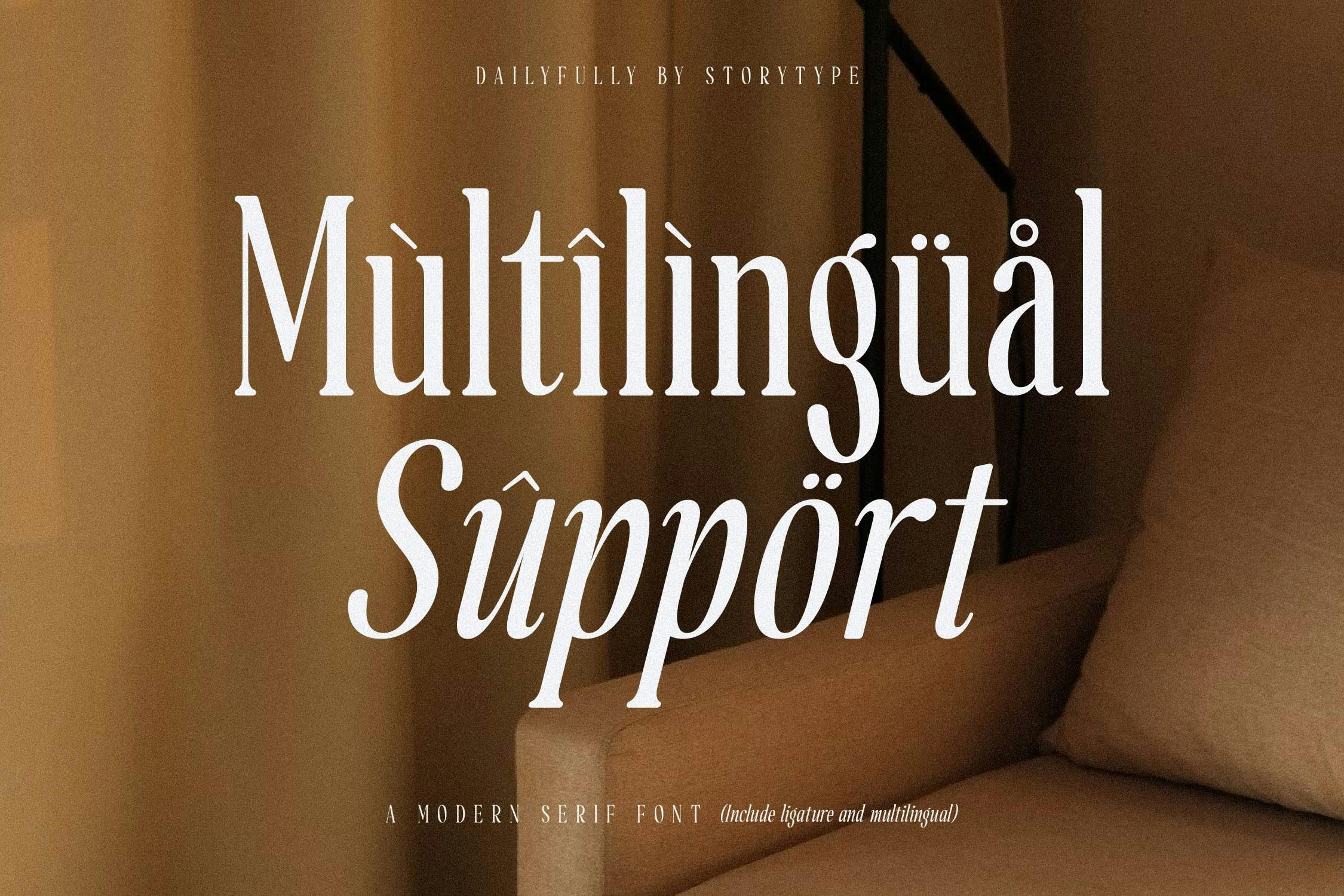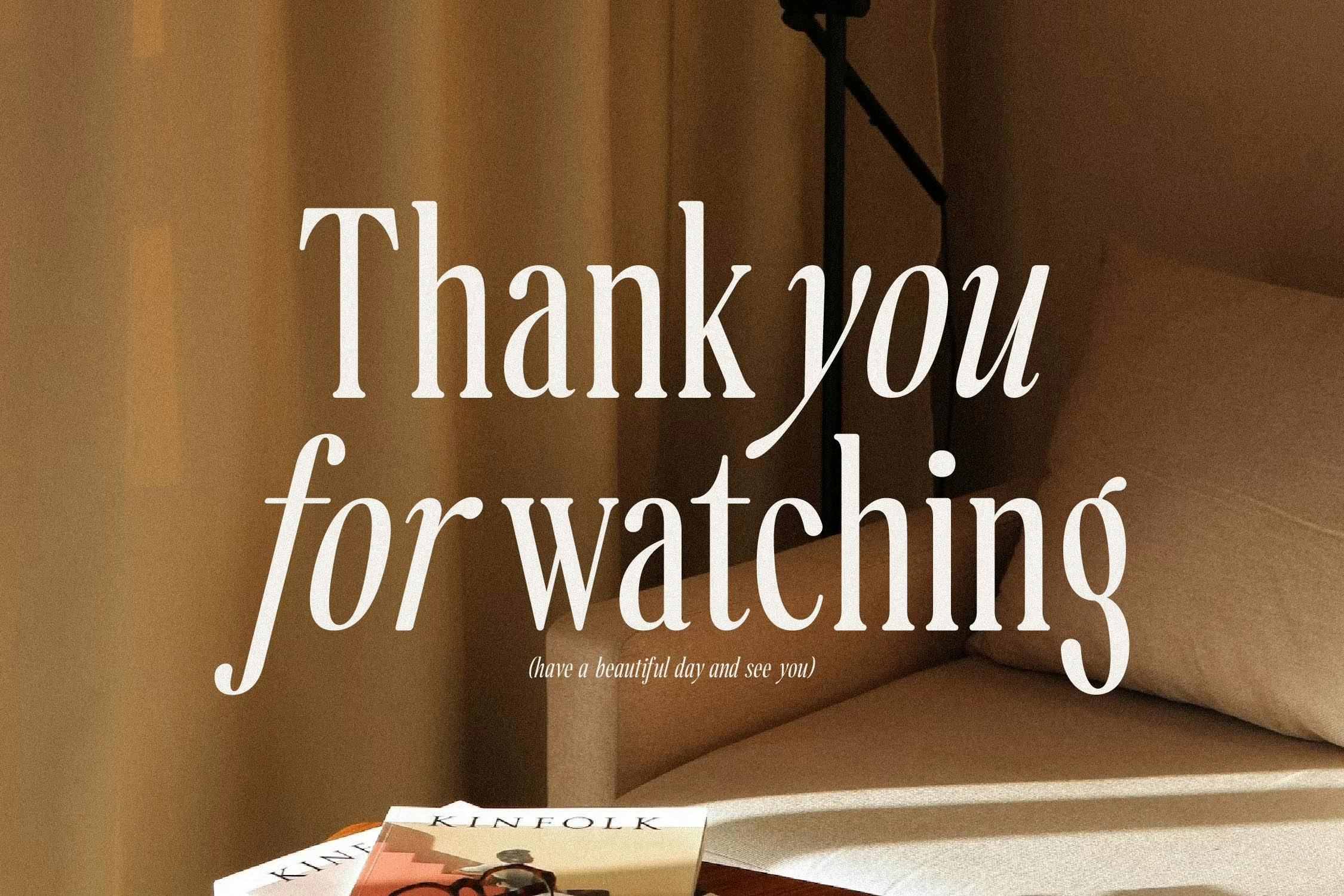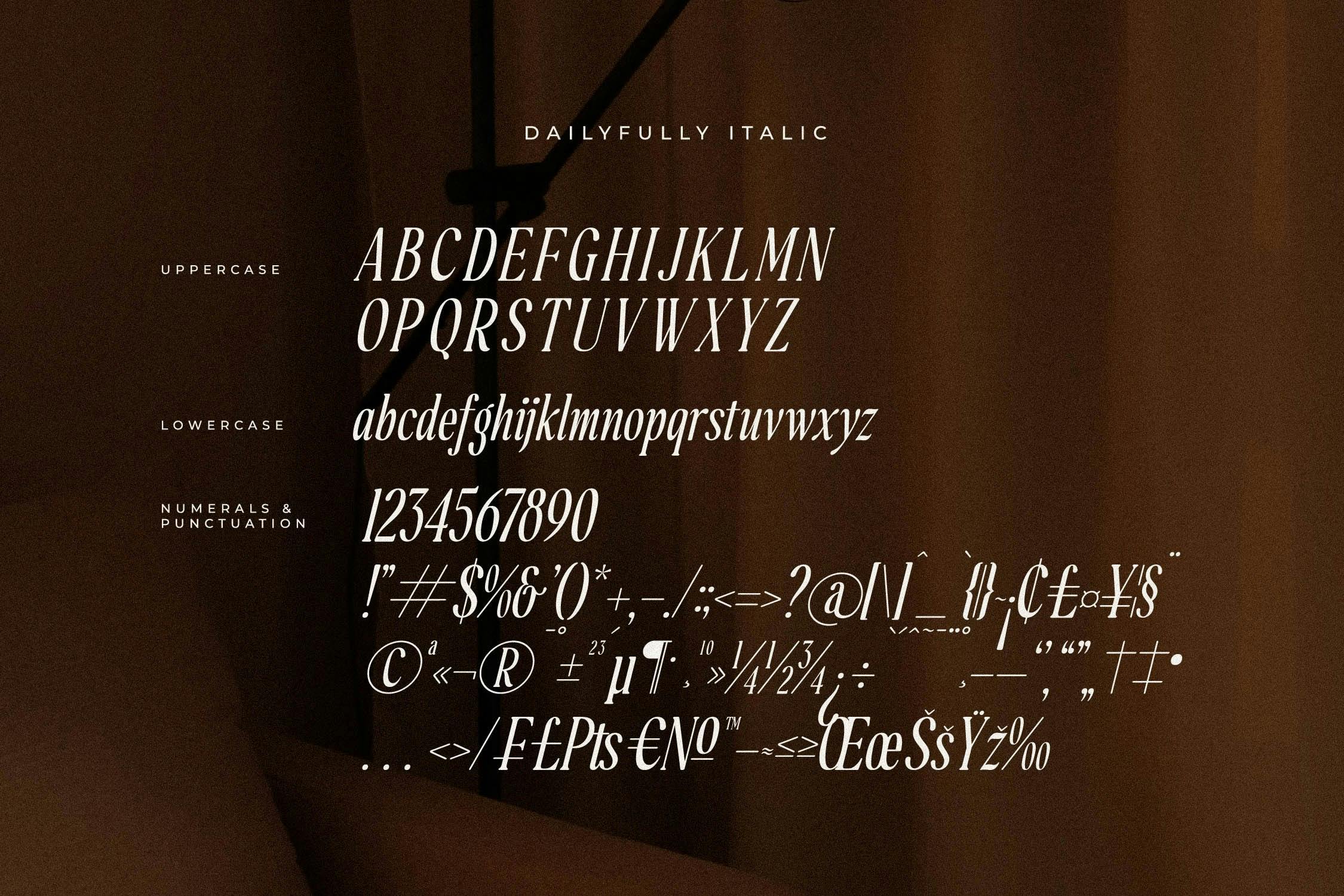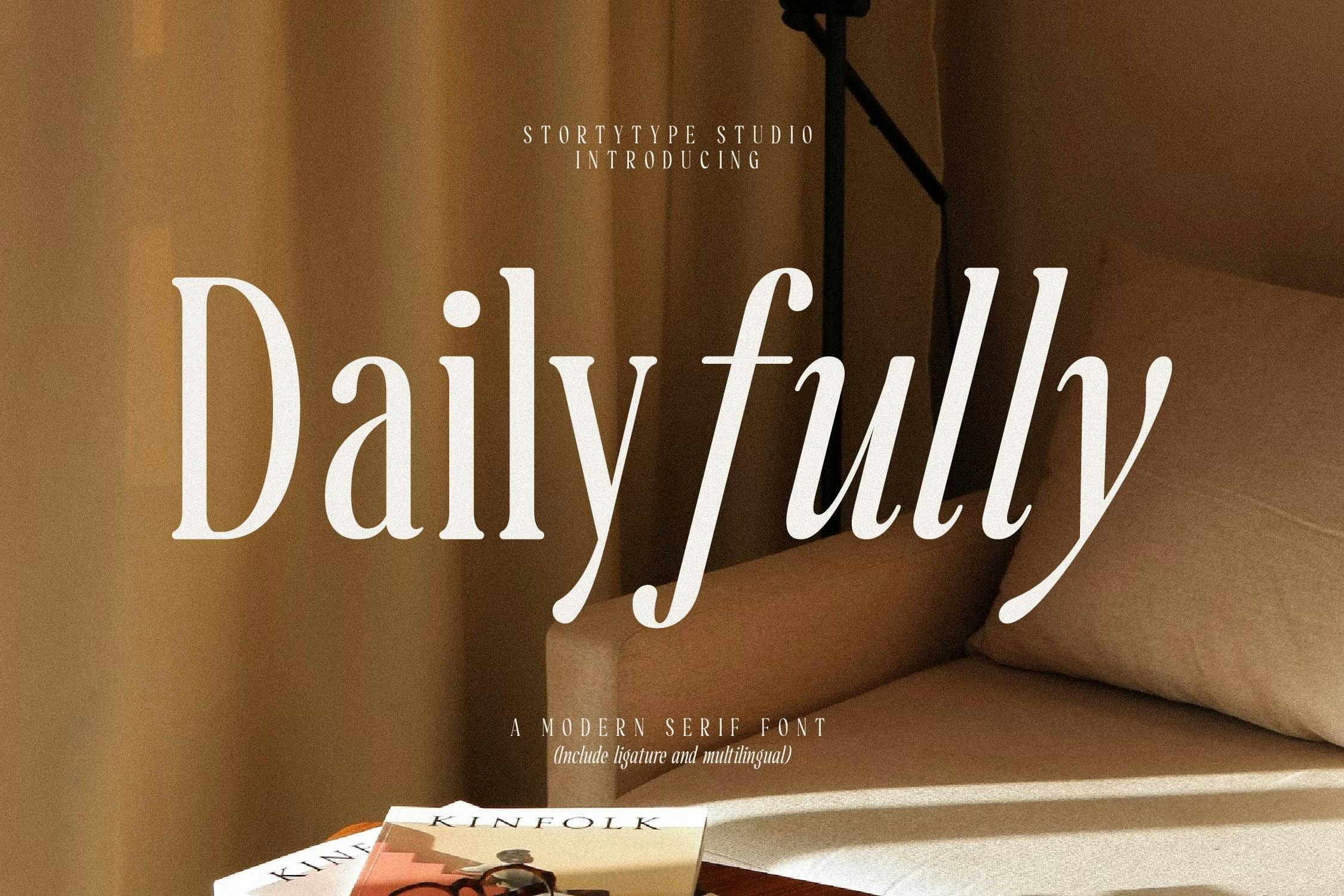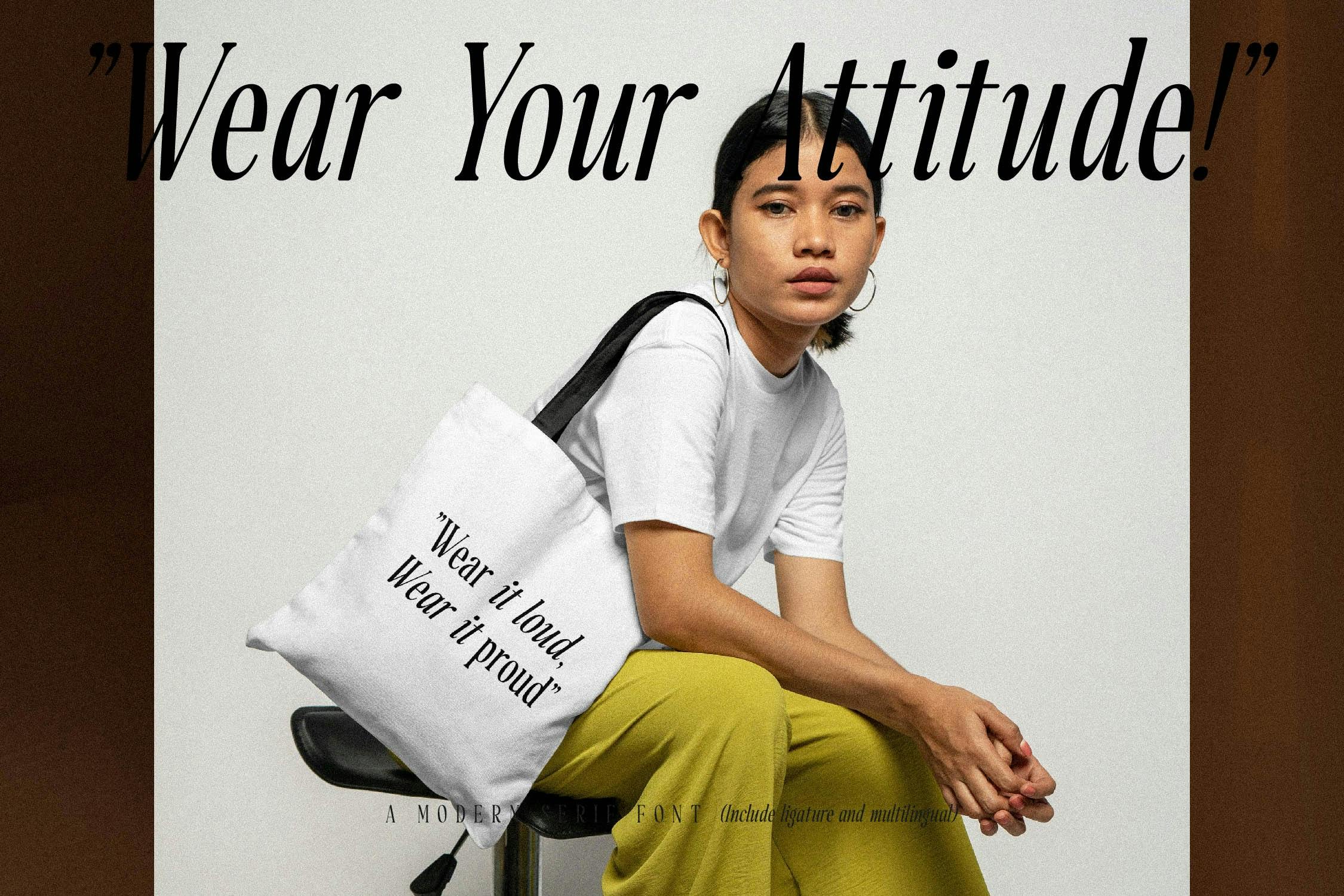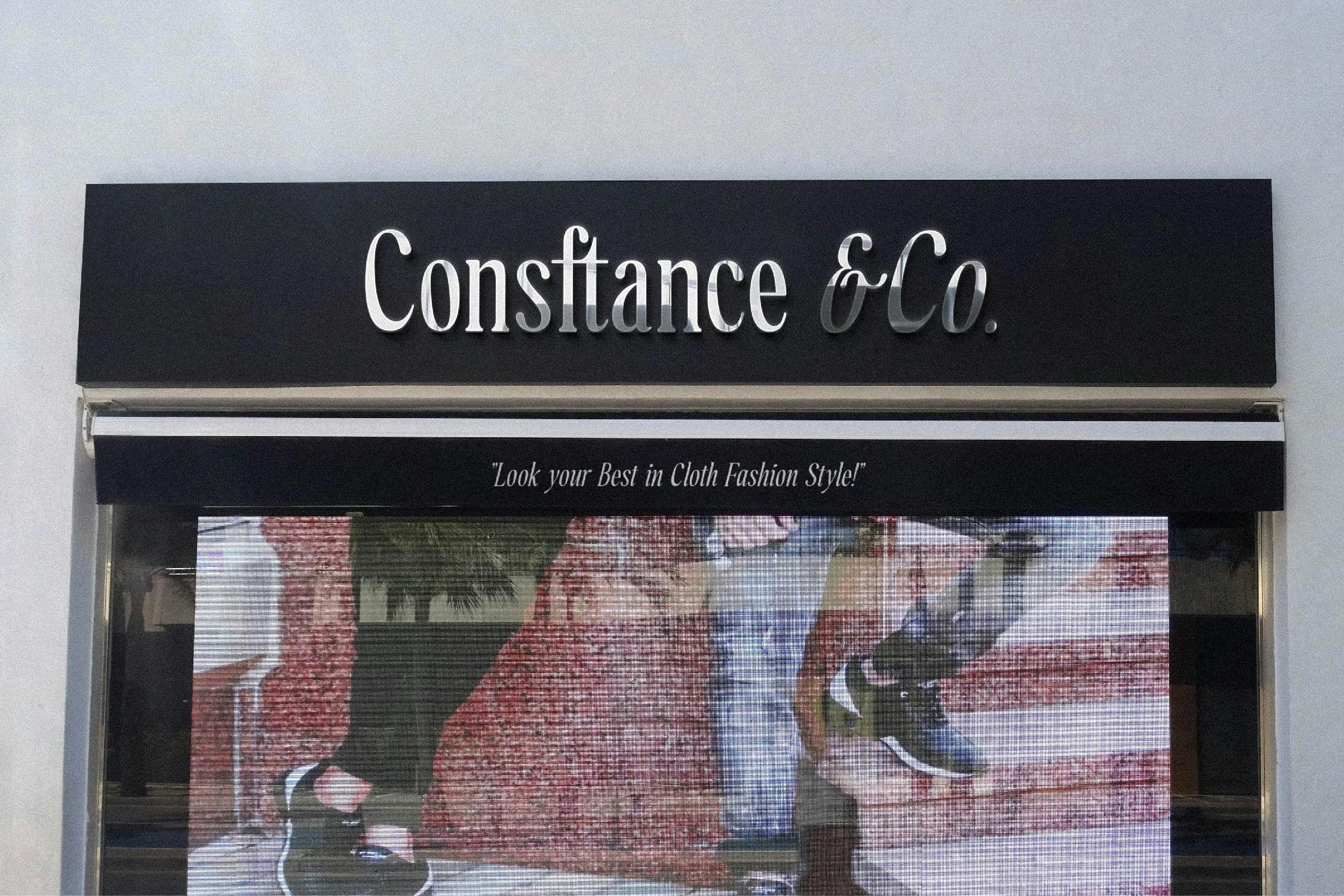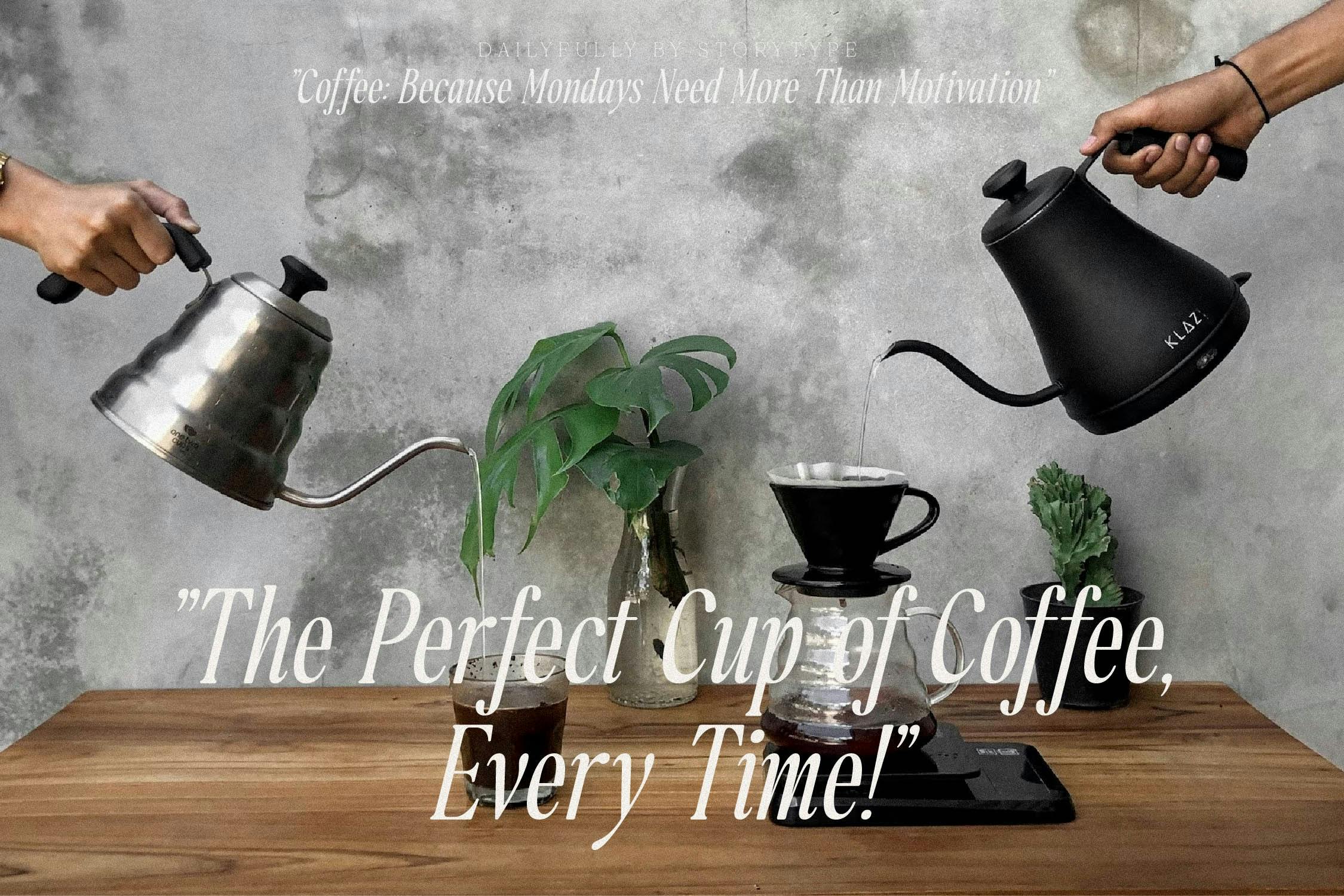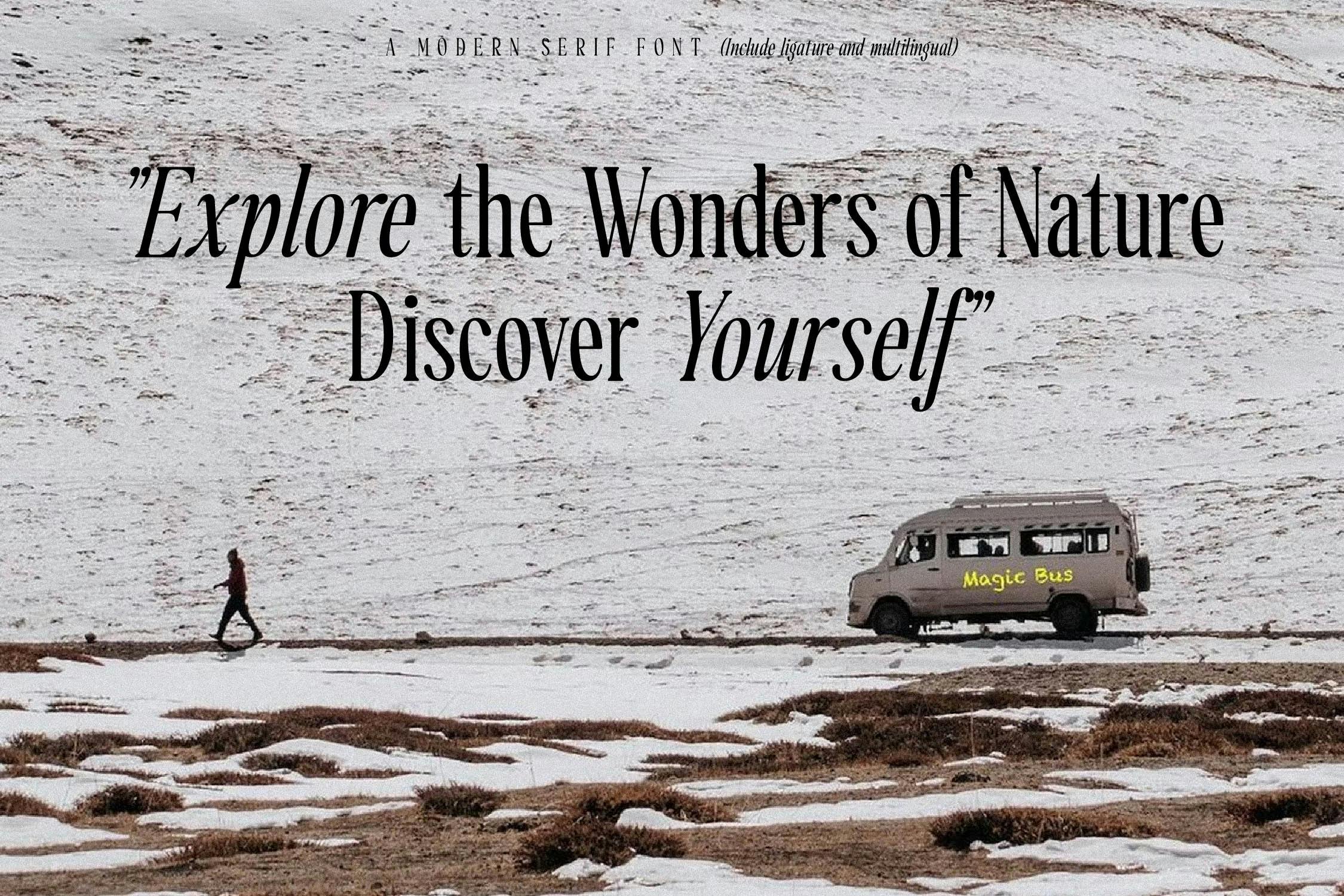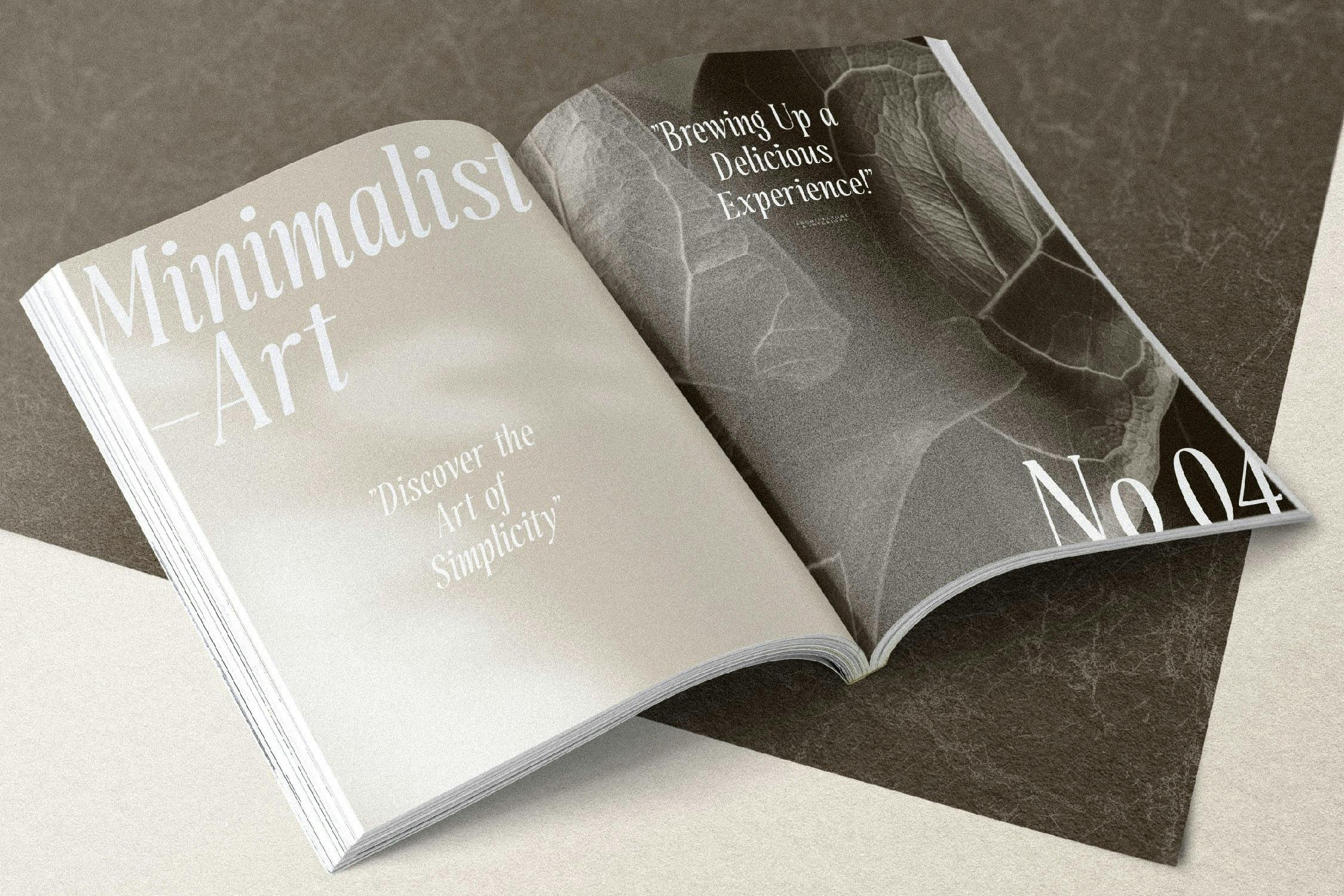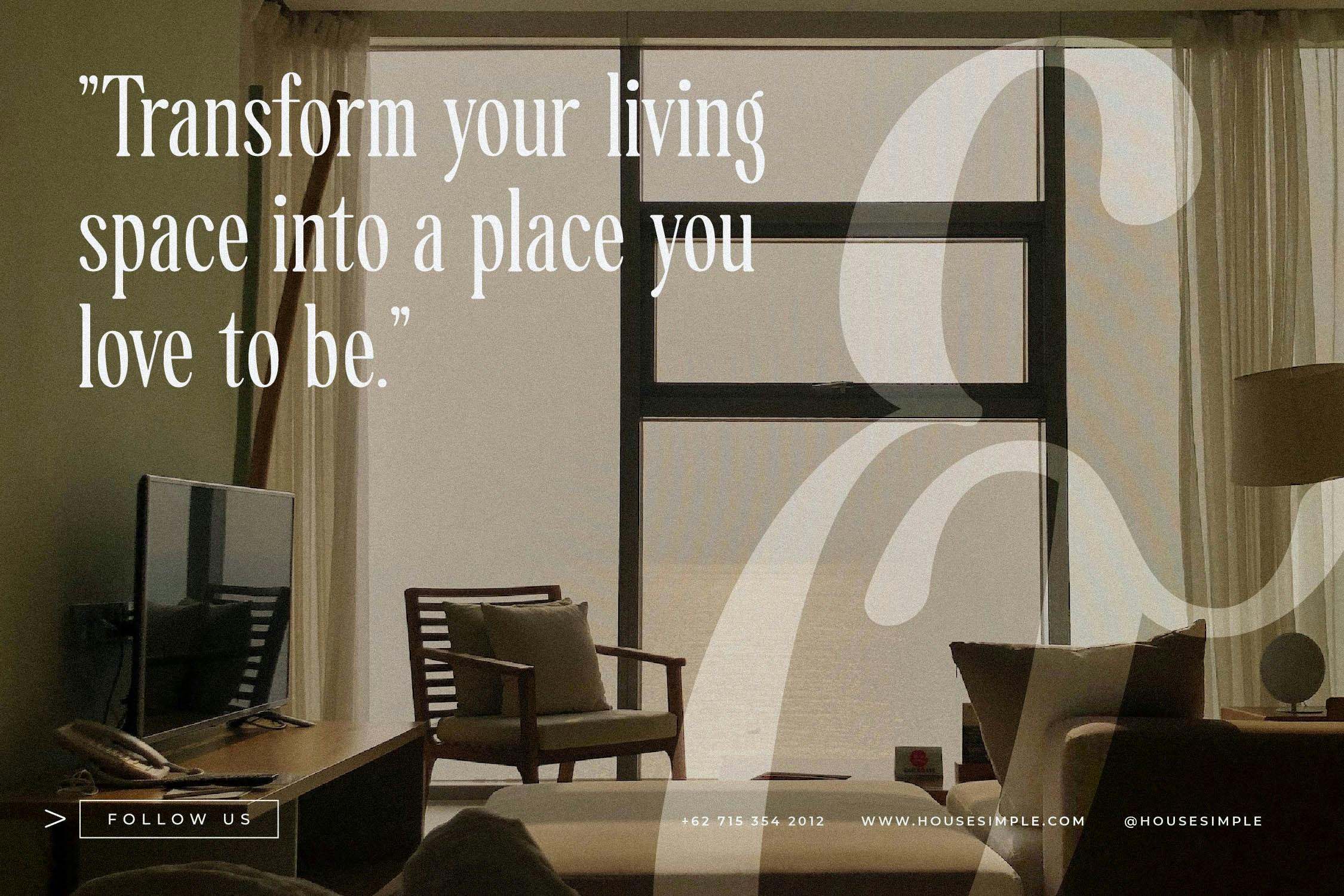
Dailyfully A Modern Serif Font
فونت Dailyfully مناسب برای طراحی‌های دیجیتال و چاپی شما.
سلام خانم‌ها و آقایان، این یکی از فونت‌های ماست که برای تکمیل محصولات خلاقانه دیجیتال و چاپی شما مناسب است.
این فونت برای طراحی پوسترها، پست‌های شبکه‌های اجتماعی، برندینگ و پروژه‌های شخصی ایده‌آل است.